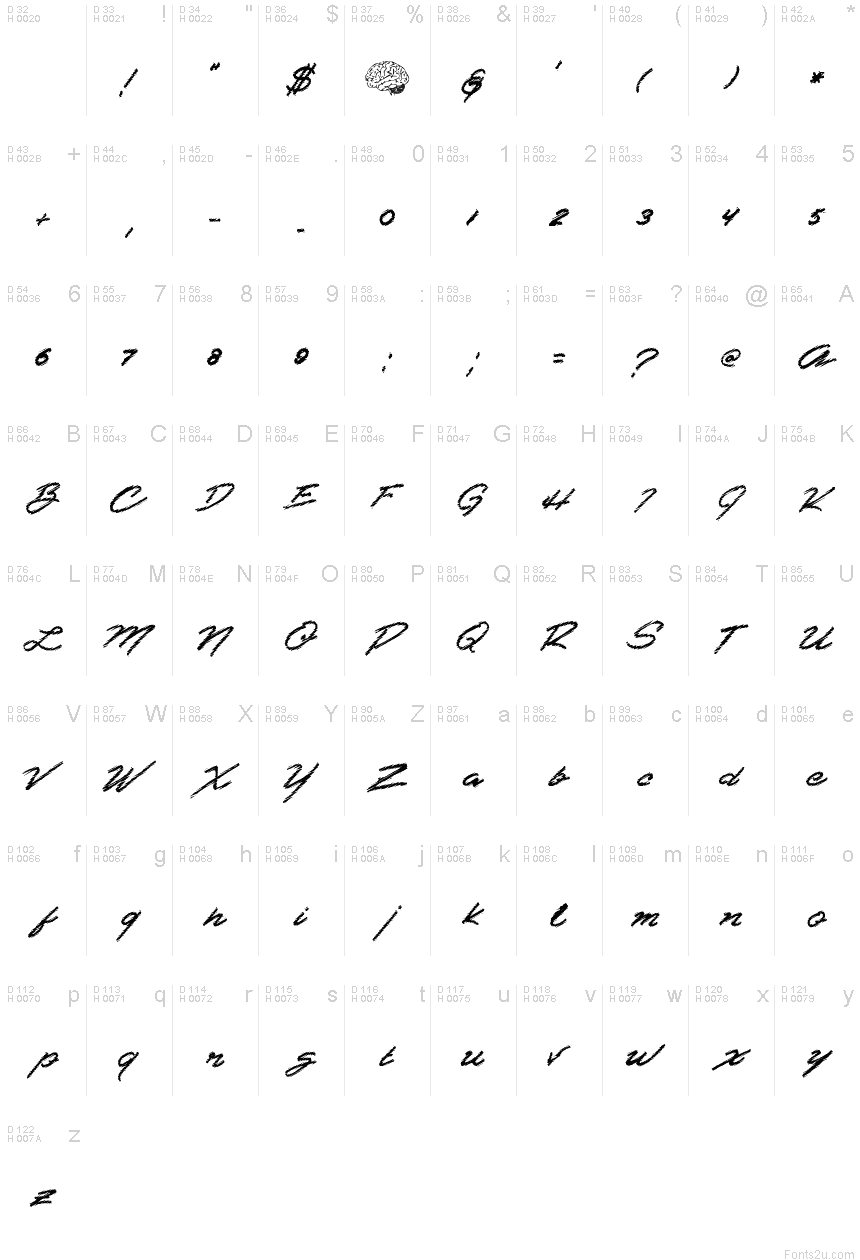
Shredder od Brain Stew Fonts to darmowy, „poszarpany” skrypt, który sprawia wrażenie szybko nakreślonego zużytym markerem lub suchym pędzlem. Litery mają postrzępione krawędzie i połamane kreski, co nadaje krojowi nerwowej, grunge’owej energii, zamiast wygładzonego pisma odręcznego.
Idealnie sprawdzi się w skejtowych zinach, na plakatach zespołów, w horrorowych nagłówkach, na okładkach mixtape’ów czy w surowej grafice streetwearowej, gdzie darmowy font z taką dawką chropowatości zdziała więcej niż czysty skrypt. Użyj go do krótkich nagłówków, szkiców logo czy tekstów na okładkach, gdy chcesz, by pismo wyglądało na przetarte, niespokojne i nieco zadziorne.